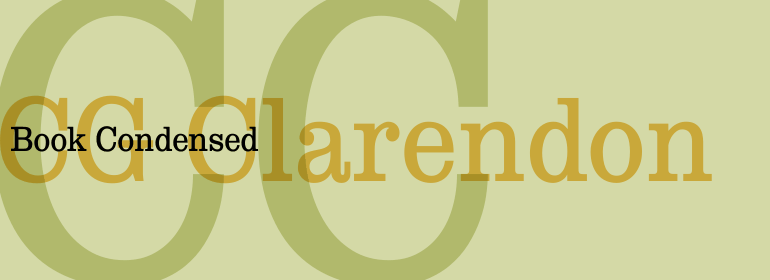
CG Clarendon®
CG Clarendon®,这款字体结构工整、笔画清晰,兼顾美观与易读性,适用于标题、正文、海报、包装、LOGO 等多种场景。字形优雅稳定,风格百搭耐看,适配日常排版与创意设计,让文字呈现更舒适、更具质感。CG Clarendon®一笔一画,皆是细节,以均衡的比例、流畅的线条打造舒适视觉体验,字形端正大气,风格简约现代。无论是商业设计、品牌宣传还是日常排版,都能轻松驾驭,让文字更有格调与力量。CG Clarendon®字体下载。
字体品牌: Monotype 设计师:Compugraphic Design Studio 字体分类:衬线体 字体属性:外文 字符集:Unicode 发布时间: 2018